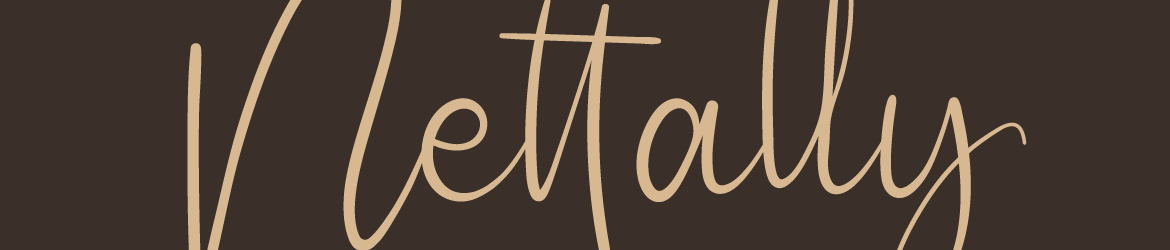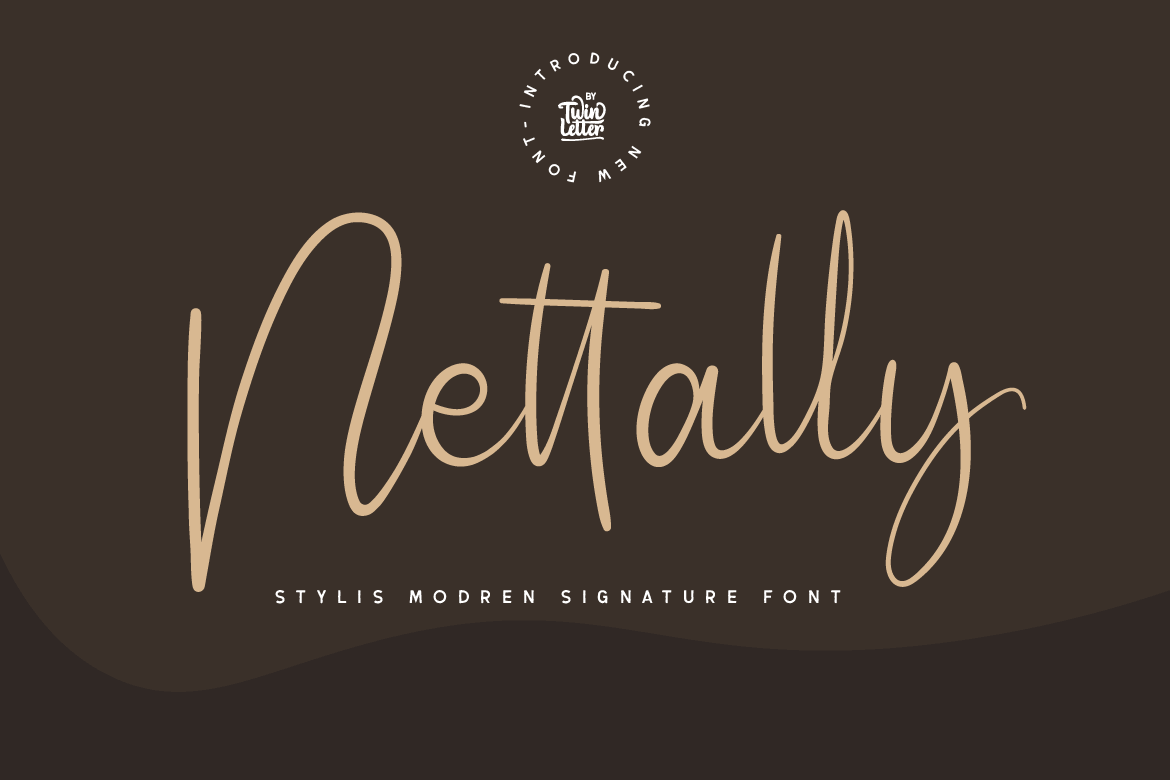
Nettally Font – Fonte Grátis
Nettally Font
A Nettally Font é uma elegante seleção de letras que oferece uma sensação de delicadeza e feminilidade na forma de assinaturas. Ela captura a essência de um estilo simples e charmoso, proporcionando um sentimento de sofisticação e encanto. Perfeita para projetos digitais variados, esta fonte é ideal para uso em logotipos, cartões de aniversário ou mesmo na criação de artigos publicitários. Ideal tanto para designer profissional quanto iniciante, a Nettally oferece um toque suave e envolvente que certamente impressionará seu público-alvo. Que tal experimentar a delicadeza desta fonte neste próximo projeto?